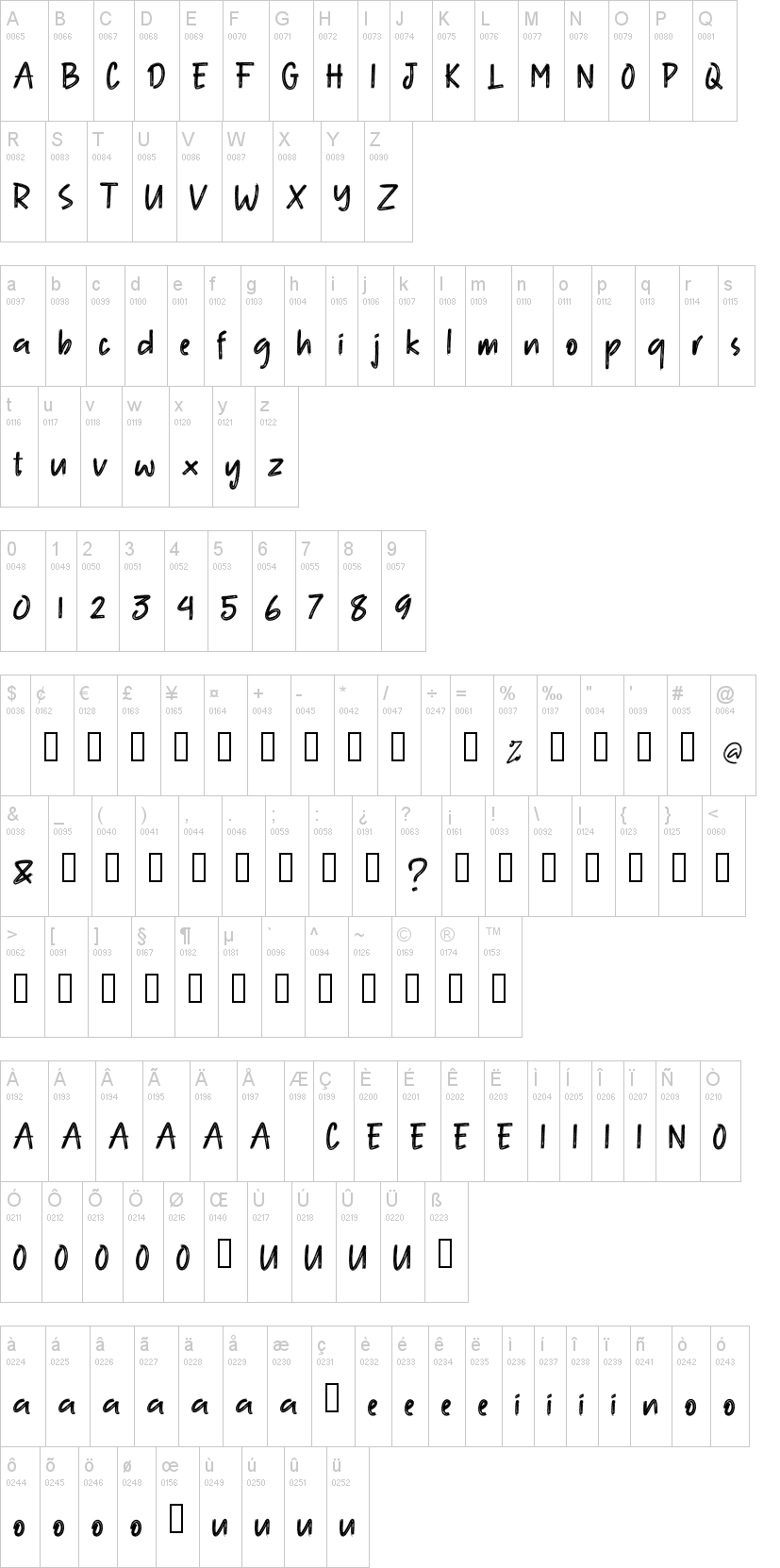
Spider Brush 是一款由设计师Milena Brandao设计的手写字体,它的特点是拥有流畅的线条,温柔的笔触和清晰的字形,适合用于各种设计场景,特别是用于创建时尚、可爱和浪漫的文字效果。它有多种字重,可以满足不同的需求,并且可以自由组合,以获得最佳的视觉效果。内容介绍
Spider Brush是一款非常不错的手写艺术字体,具有很好的视觉感,适合于文化类的宣传设计、商业类品牌的广告和产品包装设计以及个性化文字排版等较多场景。